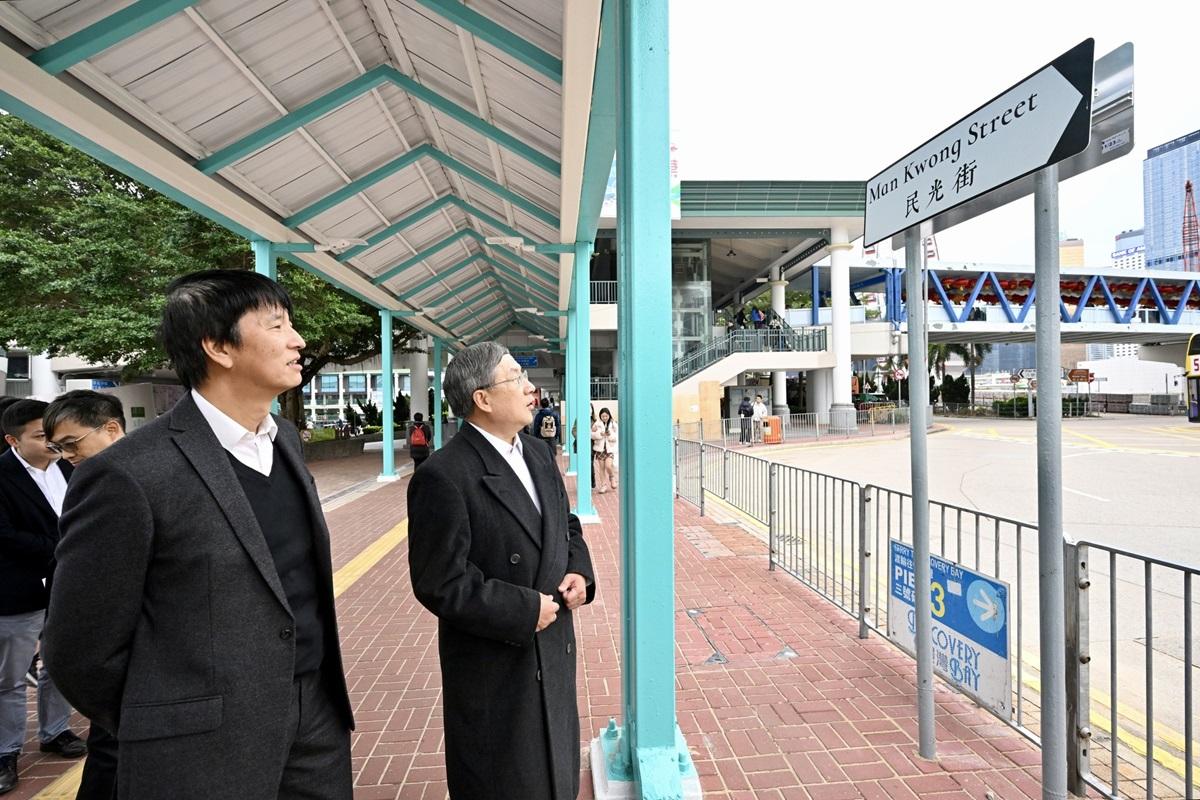
中環荃灣等地擬展開街景美化 路牌轉字體「注入文化氣息」
中環港外線碼頭一帶擬展開「小區街景美化工作」。(資料圖片)
現屆政府上任初期成立「地區事項統籌工作組」,除打擊衞生黑點亦已展開改善市容工作。路政署計劃今年為3個人流較高的地點進行「小區街景美化工作」,包括中環港外線碼頭、大圍港鐵站和荃灣路德圍,希望以提升社區景觀和氣象。
字體擬改「文悦古典明朝體」
政府向立法會委員會提交文件指,該3個地點的街名牌字體為「全真字庫(港人版)—粗黑」,計劃日後將之改為「文悦古典明朝體」,冀為路牌「注入較為濃厚的文化氣息或氛圍」。除更換街名牌字體外,其餘美化工作包括更換欄杆、行人路磚和渠蓋,並會美化有蓋行人道和街燈燈柱等。
指定地點的街道名牌計劃轉字體,以「注入較為濃厚的文化氣息或氛圍」。(立法會文件截圖)